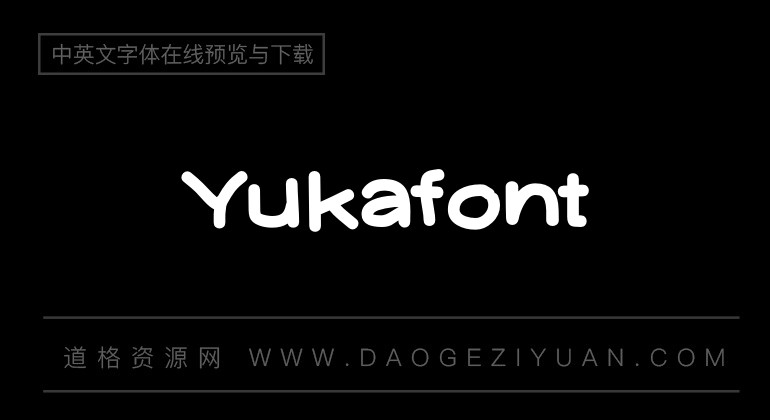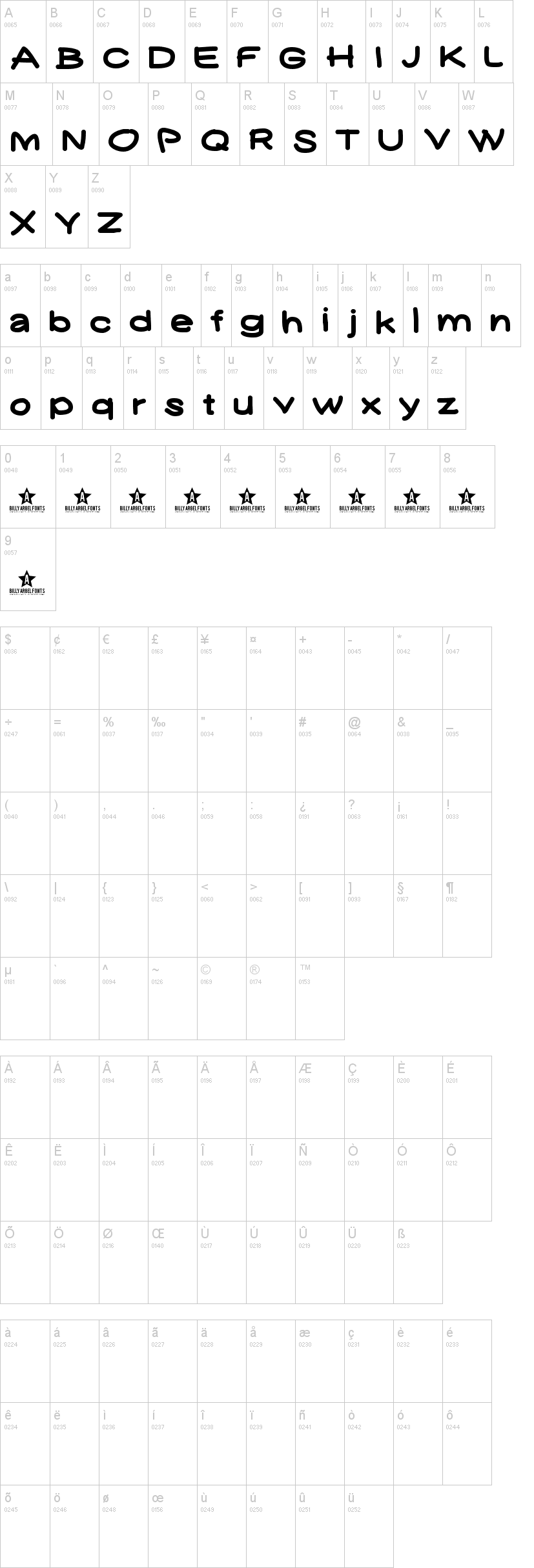
Yukafont
Yukafont 是一款清新时尚的日文字体,由日本设计师Yuka Yamada设计,拥有清晰的曲线和细腻的细节,为您的文字提供了优雅的外观。它的字体结构极其简单,可以让文字更加清晰明了,而且可以轻松地搭配其他字体,让您的文字更具表现力。Yukafont 适用于所有类型的文字,包括日语、英语、中文等,可以让您的文字更加优雅而又时尚。
Yukafont是一款非常不错的手写艺术字体,具有很好的视觉感,适合于文化类的宣传设计、商业类品牌的广告和产品包装设计以及个性化文字排版等较多场景。
Yukafont字符映射图